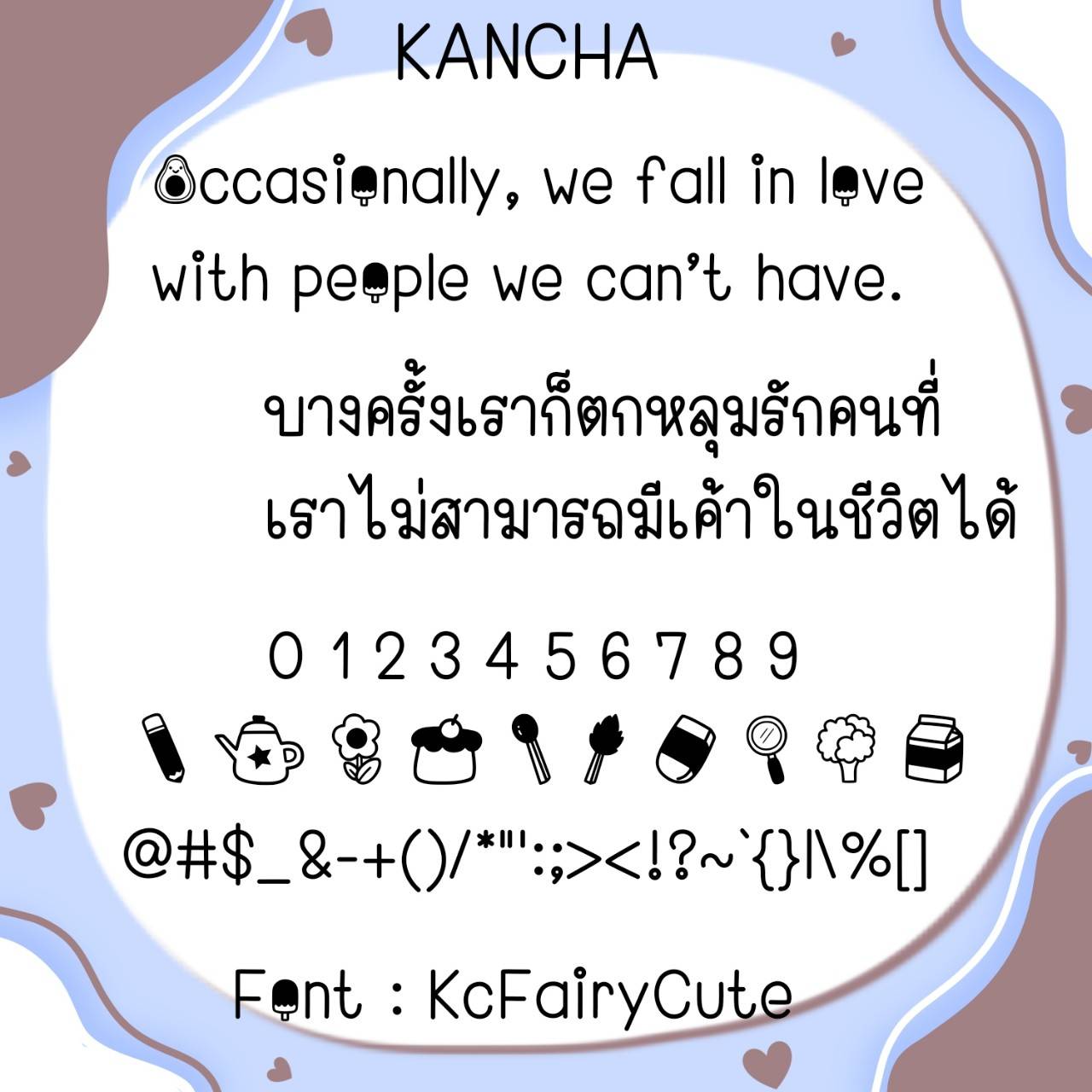
Font KcFairy
ชื่อสินค้า : Font KcFairy 💙
🔸ฟอนต์แนวหัวโตตัวผอม แต่ยังมีความดูเป็นระเบียบ อ่านง่าย กึ่งสไตล์วัยรุ่น และยังมีอิโมจิน่ารักๆแทนเลขไทยในชุดให้ด้วยค่ะ🥰💙
🔹skinny big head font But still looks organized, easy to read, semi-teens style. And there are also cute emojis instead of Thai numbers in the set.🥰💙